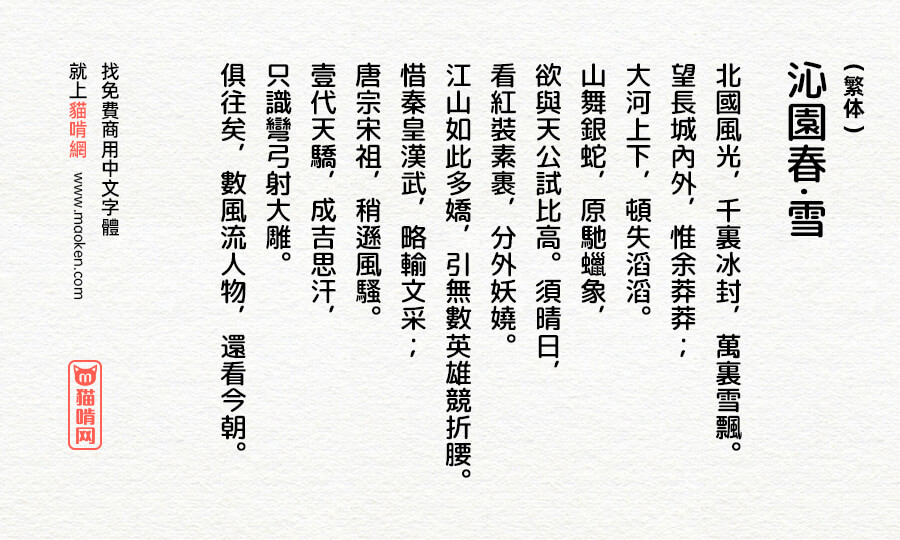
Rounded Mgen+:日本自家製フォント工房制作的圆形字体
字体名称:Rounded Mgen+PS中字体名称:Rounded-X Mgen+
字体版本:Version 1.059.20150602收录汉字:简体★★★ / 繁体★★★★★
Rounded Mgen+ (日文名:ラウンデッド ムゲンプラス) 是以日本免费商用字体“M+OUTLINE FONTS”为基础进行圆角加工改造而成的字体,而本站之前介绍的源柔黑体(日文名:源柔ゴシック)也是以“M+OUTLINE FONTS”为基础进行扩展而成的字体。
Rounded Mgen+大约包含14000个字符以上,包括日文标准JIS第1-4水准,并且,也提供了几个版本的变化。分别是标准版、L、X。它们的区别在于圆角的圆润程度不同,L 圆角最小 (最尖),X 圆角最大 (最圆),而标准版则是介于两者之间。每个版本都有 7 种字重,3种字形样式 (包括等宽字体),大家可以根据喜好选择使用。
这款字体从本质上跟思源柔黑体并没有太大的区别,而且字符集是以日本的JIS水准为标准,所以对简体中文的支持度较差,对繁体中文支持度较好。虽然是免费商用的,但是本站也不推荐使用,因为对于我们国内的设计师,有另外一套也是基于思源思体而开发的圆形字体可以选择,那就是中国台湾设计师捣鼓出来的“源泉圆体”,对于简体和繁体的支持度比思源柔黑和这款Rounded Mgen+更好。
与自制的圆形M+的区别
• 自家製 Rounded M+中未包括的汉字和符号由修改后的思源黑体补充,从而使字符数量相当于JIS X 0213:2004。
• 在JIS 2004中改变的字符集现在是标准化的。 使用兼容的软件,有可能切换到JIS90字体。
• 平假名、片假名和一些全角符号现在可以用比例宽度系列(1cp / 1pp / 2cp / 2pp)。